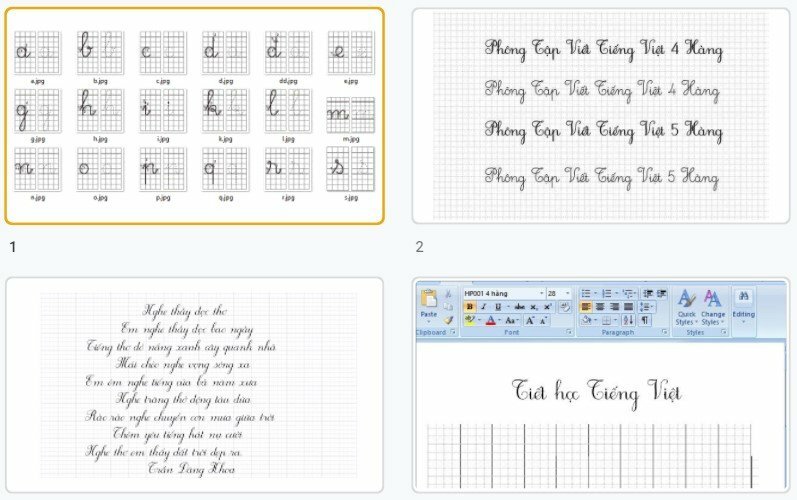
Tổng hợp font chữ tiểu học miễn phí
Font chữ tiểu học nằm trong bộ font chữ việt hóa. Font chữ tiểu học thường được thiết kế để phù hợp với việc giảng dạy và học tập của trẻ em, với các đường nét đơn giản, rõ ràng và dễ đọc. Một số font chữ phổ biến cho đối tượng này bao gồm VNTime, Comic Sans, và Linh hoạt. Các font này thường có các ký tự to, dễ nhận diện, giúp các em học sinh tập trung vào việc học chữ cái và viết văn bản. Đặc biệt, font được thiết kế gần giống với chữ viết tay tiêu chuẩn, rất phù hợp cho việc học viết trong các lớp tiểu học. Sử dụng font chữ tiểu học đúng cách sẽ hỗ trợ quá trình học tập và tạo sự hứng thú cho trẻ.